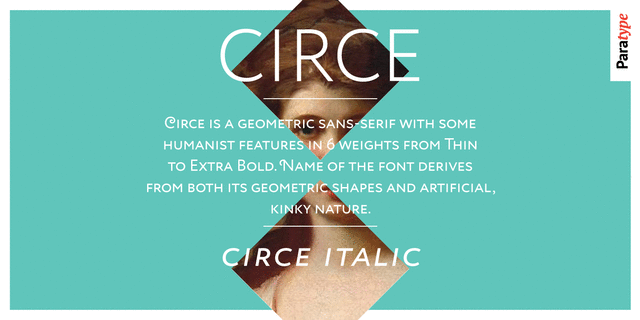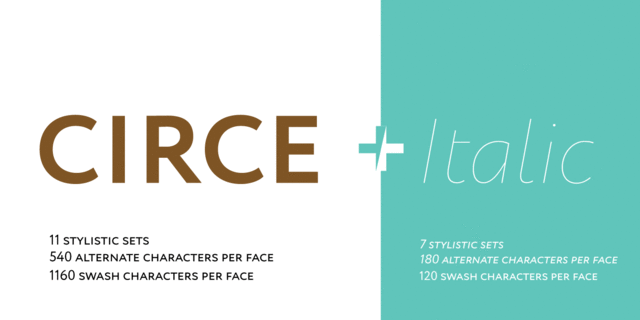
Circe — геометрический гротеск с человеческим лицом и многочисленными приятными дополнениями. Гарнитура состоит из 6 начертаний разной насыщенности, от тонкого до сверхжирного. Своим именем шрифт обязан как геометричности форм и процессу создания, превращённому в массовое развлечение, так и своеобразному, несколько опасному характеру. В то время как базовые формы Circe представляют собой достаточно спокойный геометрический гротеск с некоторыми гуманистическими чертами, альтернативные формы и знаки с росчерками могут полностью изменить характер шрифта. С одной стороны, дизайнер может наслаждаться невиданным до этого в кириллице разнообразием форм, но, с другой стороны, единственным ограничением для всего этого разнообразия служит только вкус и здравый смысл пользователя, так что в какой-то мере шрифт становится для него опасным, как колдунья Цирцея для Одиссеевых матросов. Сверхрасширенный знаковый состав Circe, включающий в себя как знаки для большинства европейских языков на основе латиницы и кириллицы, так и огромное количество альтернативных вариантов и вариантов с росчерками, организован в стилистические сеты, позволяющие быстро, удобно и гибко менять характер набора. Шрифт хорош как в достаточно мелком текстовом наборе, так и в крупных кеглях, например, в журнальных заголовках, плакатах и т.п. Дизайнер — Александра Королькова. Шрифт выпущен компанией ПараТайп в 2011 году. Курсивные начертания добавлены в 2018 году Александрой Корольковой и Марией Харламовой (Селезеневой).